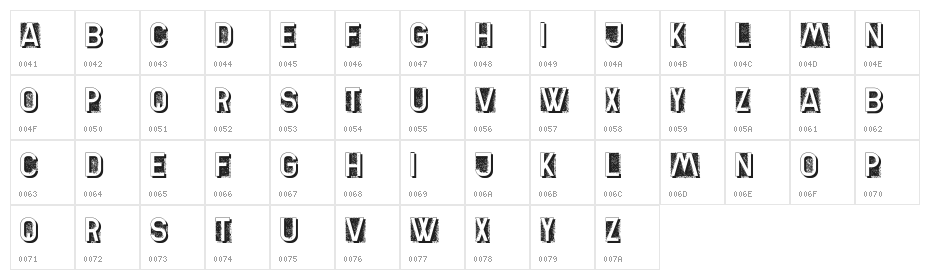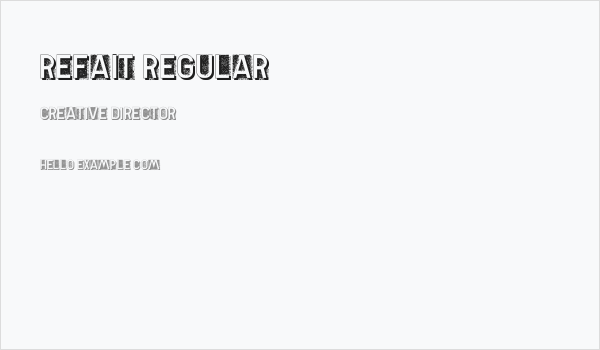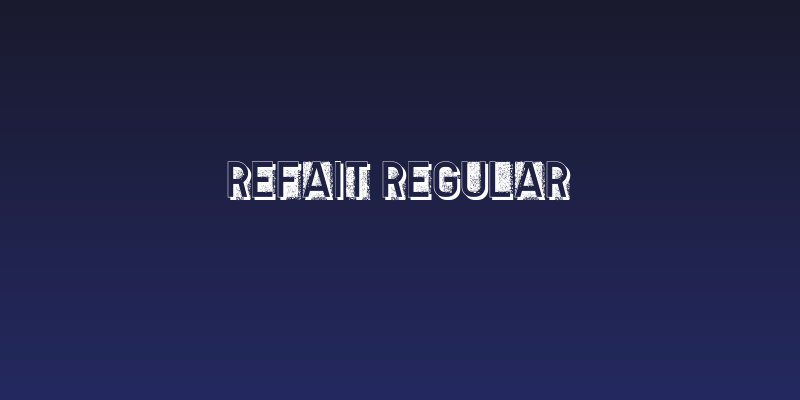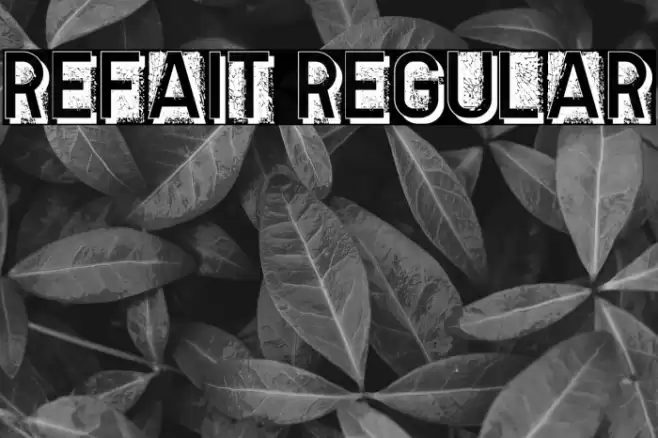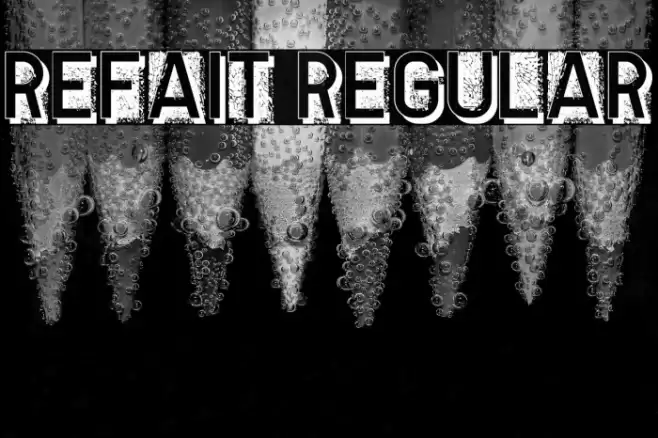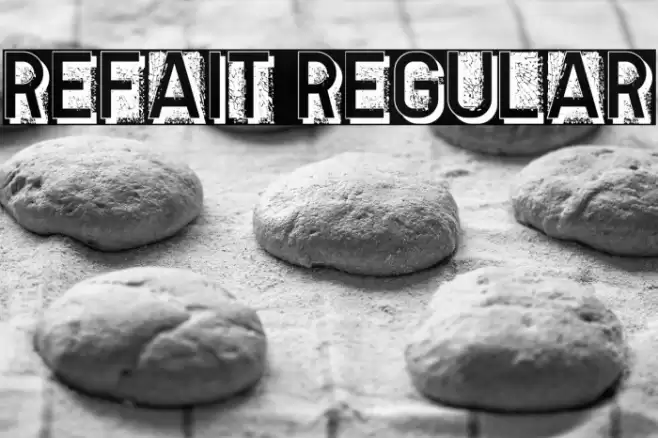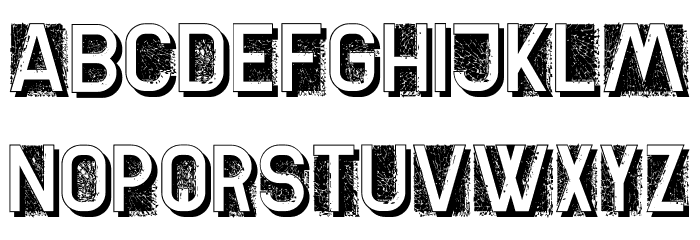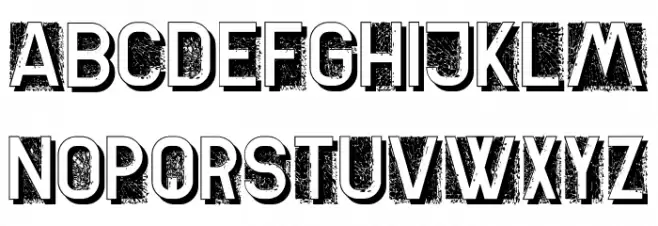
Refait Regular Font
| Projetos propostos | Ideal for poster designs, album covers, branding for edgy or vintage-themed products, and any project requiring a bold, artistic statement. |